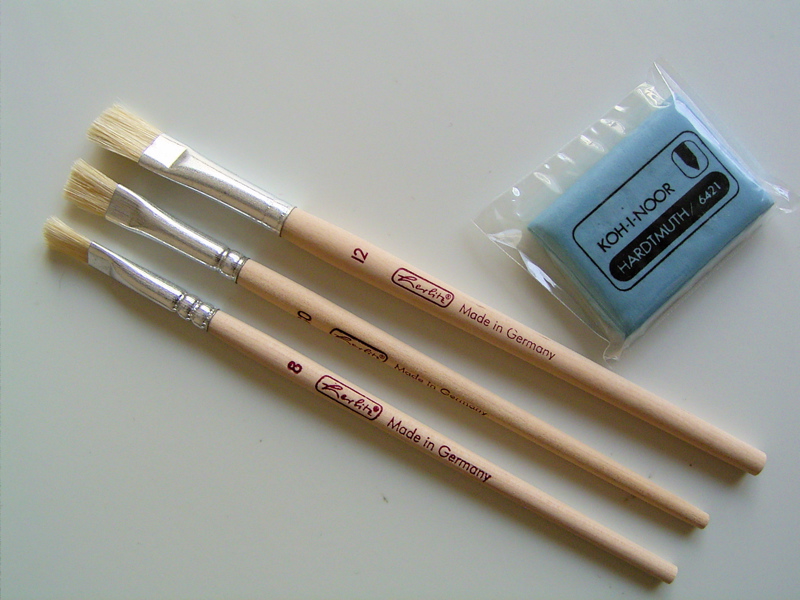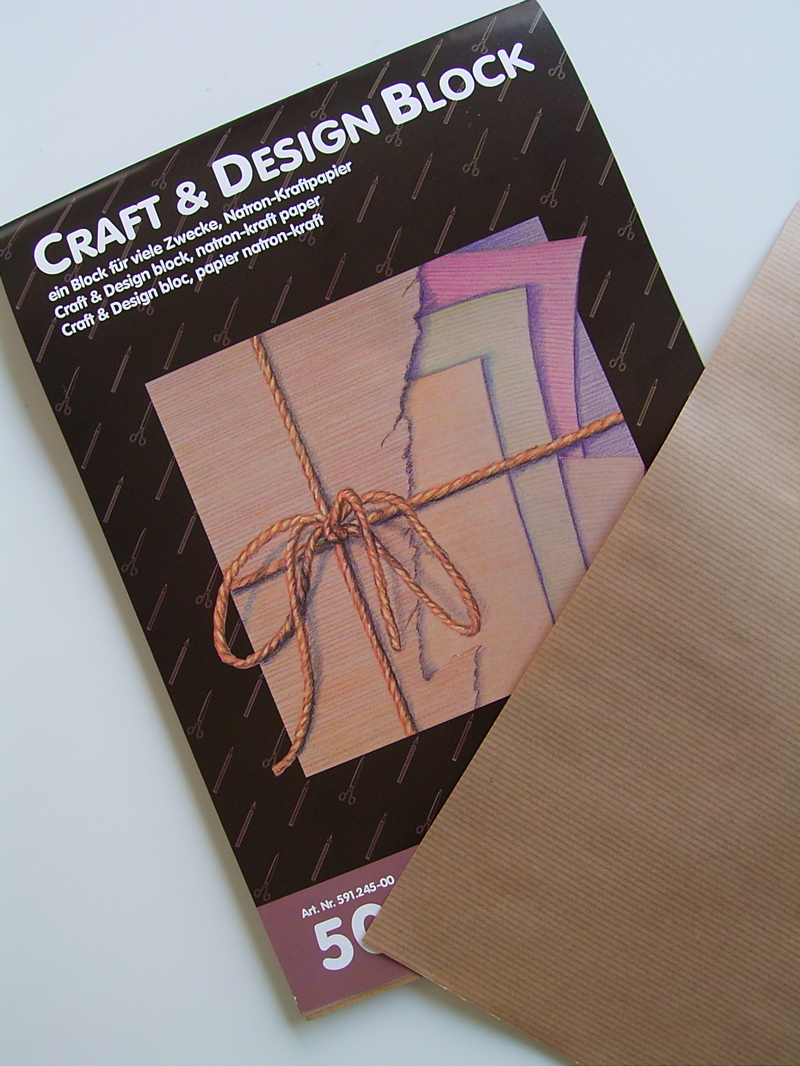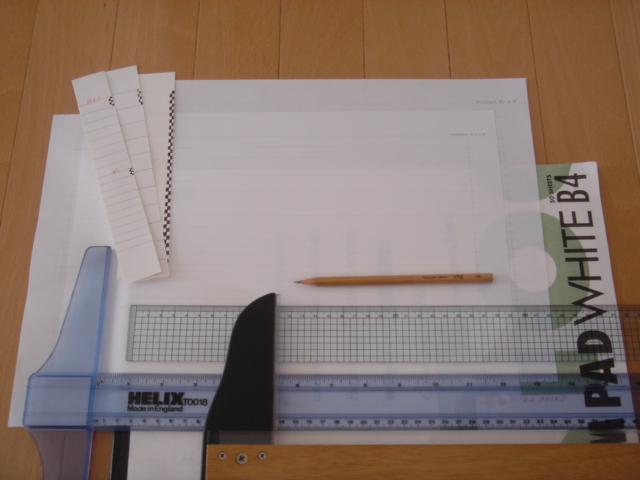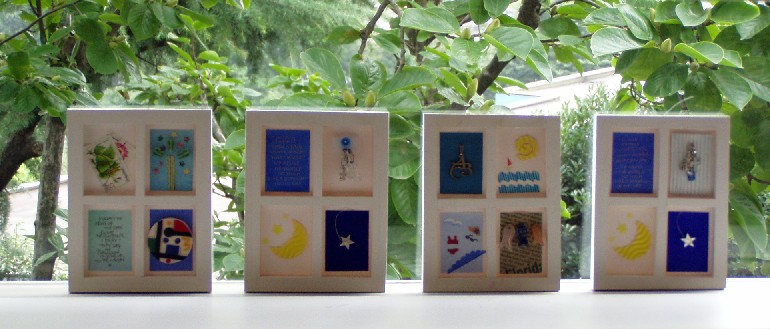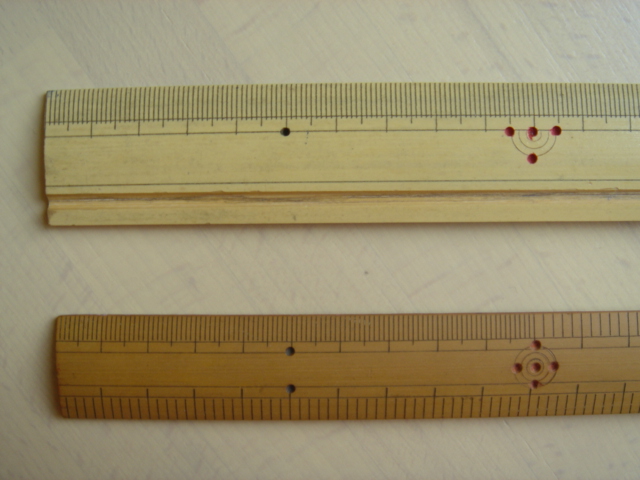
いざ京橋へ!
今日は作品展の搬入日です!
眠い…眠い…最後まで雑用…。みんな準備は万端なの?
パッキングが済んだ作品…データはずいぶんと前に出したから、
ちょこっと違うのもあるかも…それもこれも前日までやってるから
ですね…。いけませんね〜。余裕なくって・・・ほら、やっぱり額装
に出している時間なかったじゃない…。やばいでしょう…。
貼れパネ作品になってしまったとさ〜〜〜。でもあんまり気にしてないのも事実…。流されるタイプでしょうか…。
今回は販売もあるので…またこれも時間かかりましたねぇ〜。
みんなはどんなもの作っているのでしょうか…?
さぁ、元気を出して…いやいや、ちゃんと起きて搬入へGo!です。
裏方としては、まだまだ気になることもありますが、とにかく
「いざ京橋へ!」
今日は九州や四国の遠方からもお手伝いの方がいらっしゃいます。嬉しいですね〜。
搬入日の醍醐味は!いろんな所から集まってきた作品たちを
一斉に包みから出した瞬間ですね〜。
作品を通して、みんなの世界に触れられます。あっ!なんだか元気が出てきた〜。行ってきます!
SCOS
本郷にあるSCOSへ行きました。よく行く通りなので何度か立ち寄ったことがありましたが、先日mojitor-hさんが行ったけどお休みだったと聞いていたし、Penの文具特集の記事にもなっていたので、フラっと行ってみました。
そこでみつけたのは、大きなトートバッグ。
色と模様が私好み!メジャーやカップやSCOSのロゴが可愛いね〜。
あとは固い毛の小さめな筆。アクリル絵具等を塗るのに良さそう。丈が短いので使いやすそう。3本で1000円位でした。
それから、クラフトペーペー。A4サイズくらいで便せんの様に一枚ずつ使えます。文字を書いたらどうかなーと思いましたが、これには失敗。ボテボテ+ニジニジになってしまいました・・・・・
きっと何かを包んだりするのにはいいかもね。
雑誌によく紹介されているせいか、ちいさ〜いお店には人が次々と訪れます。以外と若い男性が多いのに驚き。文具好きの男性も多いんでしょうね。
小さなお店なのですが、レジに座っているご主人は見事に存在を消していてくれるので、一人で時間をかけてじっくり見る事が出来ます。その技は素晴らしい。雑貨屋さんはこれでなくっちゃね!
Bun2
いつだったか…ブログコメントでfreepaperの「Bun2」を紹介
してくださった方がいらっしゃいました。
その時は「NYのカリグラファーが載っている」という情報
だったかと思います。
ずっと気になっていたのですが、記憶が失せ…ひょんな
ことからまた思い出しました!
そこで早速HPへアクセスし、バックナンバーがもらえるのか
どうか確認!…そうなんです。手に入るんですね〜。
数日後に到着!読んでみると…文具好きにはたまらない内容です。最新ステーショナリーや
作家さんへのインタビュー…お金出してもいいような充実した内容でした!
おまけにあのTVチャンピオンの「文房具通選手権」で3連覇した高畑正幸さんの文具講座
なるものまであり、感動して読みました。
そうそう、肝心なNYのカリグラファーですが、ハイハイ、表紙の写真にも出ているカレン・
チャラタン…東京で彼女のWSに参加したのですが、コマーシャルの仕事もたくさんこなして
いるカレンが紹介されていました。嬉しい〜!
私の今一番お気に入りの文具はKOKUYOから出ている
テープのり「DOTLINER」です。和紙をコラージュするとき
にもすごく便利です。
透明な素材に糊付けするのは見えてしまうので、あえて
このドットがかわいい感じになり、じゃまではありません。
日本の文房具って凄い発想だなぁ〜と感心してしまう
一品なのでありました!
ペーストペーパー
夏なのでペーストペーパーのワークショップです。
暑いと乾きも早いし、道具を洗ったり水を何度も使っても苦になりません。
大勢で作るから色数も豊富。みんなちょっとずつ違います。
こうして一日中夢中になって何枚も作ると、夕方どーっと疲れが・・・・・。でも出来上がった紙に満足満足!いろいろ出来たなぁ〜。
紙だけでも素敵ですが、これを封筒やカードに仕立てても楽しいのが、ペーストペーパーの良い所。どんなに小さくても何かになる!
さて、こうして作ったものは、実は来週から始まるアルファクラブ作品展にて販売の予定。(昨日mojitor-hさんがご紹介したカリグラフィー作品展です)
どんな物に変身して登場するでしょう。お楽しみに〜
アルファ・クラブ作品展
これは全国のカリ愛好家が所属するアルファ・クラブが主催する
「第7回アルファ・クラブ作品展」です。
今回は初の試みが多く、まず開催が東京と福岡の2ヵ所となります。会員の作品以外に特別に海外カリグラファーによる作品も17点ほど飾られる予定です。
また、会場では出展者によるカリ関係のカードやステーショナリー、本などが販売されます。
国内、国外のカリが書けそうな紙、べラムも展示されます。福岡では会期中に海外カリ人のWSもあるそうです。
来週は梅雨明けしているでしょうか…?
弱気なmojitorメンバー発言…いまだ追い込み中…。
当日壁に作品はあるのか???
残骸は増えるばかり…。
練習すればするほど本番ではヨレヨレ…なんてこともしばしば…。
意外と最初に書いたのがよかったりして…。
でも画材は床に落とすは、インクはたれるわ…で
そうじ、片付けに時間をとられ…どうなることやら〜。
「額装はどうするの?」と聞かれたら…「額装なんて、どうにかなるものよ。」と訳のわからない答えを自分に言い聞かせやるしかないのです〜。
線引きが好きな人
カリグラフィーではまず鉛筆でアンダーラインなどにするための線を引く。ふむふむ、基本ですね。
何事も基本は大事。でも面倒に感じるのですよね。はやく応用編にいきたいなー、なんて。
線引きがきらいな人もいるでしょうね。何枚もひいていれば慣れて早くできるようになるのは確かなんですが・・・
最近カリグラフィーを始めたTさんは、線引きの話になるとニコニコになりました。
線の引き方について説明を終えますと、Tさん、「線を引くのって楽しいですよね!」とますますニコニコ。聞けば元トレーサー(自動車の図面を描いてたそうです)なのだそうで。あちゃー、専門家に説明してしまっていたのですね・・・恥ずかしい!
「鉛筆は回しながらひくときれいな線が引けますよ」とのこと。やってみると、あー、ほんとだ!
美しく引けるとうれしいものですね。
マーカーで色をつけるとき(文字ではなくて絵です)、やはり回しながら使うとムラにならないと、何かで読んだ記憶があるのですが、こういうコツがあるのですねえ。
線引き初心者のうちの小学生にも教えてあげよう。なんと言っても定規をきちんと押さえる、とか鉛筆を斜めに当てない、とかそういうことから教えないといけないのです。線引き道はなかなか険しい。
なつかしの竹のものさし、30センチ、110円。今でも小学校でこれを使っていることに驚いてしまいました。
プラスチックか何かに変わっているのかな、と・・・。目盛りに数字がないから、数え間違えていることも多いです。
この赤い模様みたいなのも変わらず、なつかしいなー。この模様(しるし?)についての由来を新聞で見かけた気がするのですが、よく読んでいなくて忘れてしまいました。どなたかご覧になりましたか?
いい色になっているほうは50センチで、ときどき縫い物のときに現役で使っています。姿勢が悪い私は子どものとき、母にこのものさしを背中に入れられたことがあります。(こわ〜)
青山、原宿ぶらり
雨ばかりの日々。久しぶり、青山、原宿をぶらり。
まず、表参道アンデルセンでランチ、いつもながらおいしいおかわり自由のパン、季節もの?枝豆入りパン、オーとっても美味!あとでケーキが待っているから、今回おかわりはなし、ちょっと心残り.........
ランチ後、根津美術館前の東青山 の立花文穂展「木のなかに森がみえる」、文字、紙、本をテーマのインスタレーションということで行ってみた。芸術新潮2月号で紹介されていた立花さんの部屋は、紙カット台に使っている碁盤がデーン、そのまわりは紙のゴミ(じゃないそうだけれど)だらけでシュール。それを知っていれば、なるほどの作品?!雑誌と新聞掲載の写真は、パリでの展示のものらしく、ちょっと違う印象〜。写真はもっとこぎれいだったもの〜
そーして、すぐ近くのアニバーサリーでお・茶!札幌の方にいただいたl'OliOliのネームカードがかわいく、検索したらアニバーサリーがやっているお店だったので、青山店に行ってみた。シュガークラフトがたくさん飾ってあって、中庭も見えるラブリーなお店。パッションのケーキは、甘酸っぱ〜い!
この26文字セットを購入されるとはすごいです。(世界堂で、だそうです)
抜いた文字がバラバラにならないように、BやDやOなど輪になっている文字はどこかが切れているんですね。ふんふん、納得。
このかわいいミニブックは青い表紙です。黄色のパンチにぴったんこ!
青い色と黄色の組み合わせっていいなあ。スウェーデンの国旗の色が大好きなんです。
伝説によると昔々の王様が青空に金の十字架の光を見たことからこの国旗ができたそうなんですが・・・黄色ではなくて金色なんですね、ほんとうは。
以前見た北欧の学校の写真で、壁や掲示版なども青色で、そこに木の机や椅子があっていい色だなあと思っていました。この組み合わせが映える、その土地の空気ってあるかもしれません。
この二色の組み合わせは画家のモネのお気に入りだったとか。庭の花の組み合わせ以外にもインテリアや食器に使っていたらしいです。
この色が主役のお話といえば、レオ・レオー二の名作「あおくんときいろちゃん」ですね。お話も、絵も、このシンプルさがいいですよねー。
この絵本、実は表紙がすてき。本屋さんにあったらそっとカバーをはずして見てみて・・・もいいですか、本屋さん?